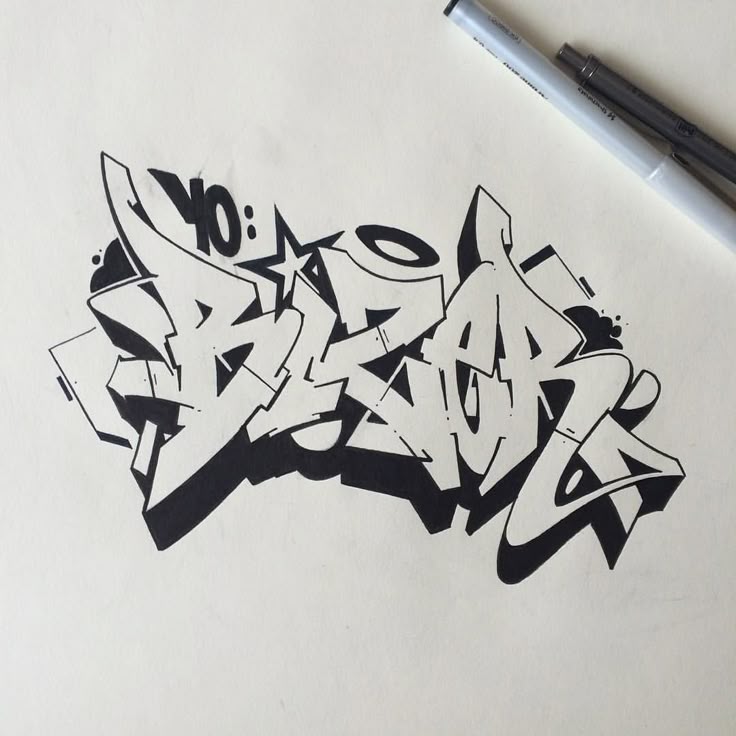
За потоком книжных новинок мы не успеваем задуматься над тем, что происходит с элементарной частицей любого издания – словом. А между тем оценка литературного процесса как “прорыва” или “кризиса” в глобальном смысле основывается на судьбе слова, его положении в современной культуре.
“Визуализация”, “визуальность” – эти понятия стали общим местом актуальной культурологии. Равно как и конкуренция между визуальной и словесной информацией, образом и словом, которое картинку только подразумевает.
Граффити, комиксы, инфографика, видеоблоги – многообразные подтверждения того факта, что слово в массовом сознании, массовом употреблении все более визуализируется. Для человека, воспитанного в прежнем, логоцентричном обществе, это не может не выглядеть унижением слова.
Но что если логоцентризм сменяется вовсе не визуальностью, а синкретизмом, сплавом художественных “языков”? Что если кажущееся унижение слова на самом деле направлено против перегородок, разделяющих разные области искусства?
В конце концов, субкультура граффити выросла из слова, в самом прикладном смысле – из авторского почерка. А визуализировать слово начала еще высокая поэзия – вспомним “рисунок стиха” Аполлинера, “лесенку” Маяковского, книжные эксперименты футуристов, фигурные стихи Вознесенского.
Материал нашего постоянного автора, искусствоведа и критика Веры Калмыковой, знакомит с языком рисованных слов.
Граффити: почерк на стене
Что может быть проще, однообразнее, скучнее, наконец, депрессивнее стены? Обычной стены в обычном городе, в чистом виде пригодной лишь для того, чтобы уставиться на нее в отчаянии. Узорная или грубая каменная кладка, деревянный или каменный же наличник, ветка чего-нибудь вечнозелено-вьющегося, нечто оживляющее, разбивающее жуткую, противную человеческой психике плоскость, – издревле известные украшения стены. Можно предположить, что первобытные наскальные рисунки несли ту же функцию, что в современном городе – граффити.
Наскальные росписи служили освоению мира. Тогда изображение воспринималось не так, как сейчас. Рисунок был не просто символом, “иконой” материального объекта – он мыслился как его неотъемлемая часть. Между художником и тем, что он изображал, через рисунок устанавливалась прочная связь, и художник – через посредника (изображение) – получал возможность непосредственно воздействовать на сам объект.
Искусство, по-видимому, не просто “вырастало из неискусства”, как принято считать, и изначально осознавалось не только как “нечто избыточное” для жизни (не пища, не тепло, не огонь, не деторождение…). Оно служило необходимым средством общения – между одной частью мира и другой. В этом его предназначение и в наши дни.
И если принять термин Якимовича как рабочий, то современные граффити – не что иное, как реплика: из первобытности в первобытность.
…Лет тридцать назад пяти-семиклассники захлебывались в упоении, рисуя на промокашках, на последних страницах или задних обложках школьных тетрадей разные слова. Именно рисуя, нарочито “толстыми”, похожими на слоников буквами, каждая из которых вдобавок словно “подлезала” под другую, из-за чего прочитать какое-нибудь “стол” или “Катя” становилось специальной работой. Разумеется, мы тогда и предположить не могли, что уже наши дети в сходном упоении станут разрисовывать (или расписывать) похожими буквами гладкие (и не очень), белые (и не очень) вертикальные поверхности зданий, бетонные заборы, гаражи et cetera. Слова “граффити” – ни с ударением на “а”, ни с ударением на “и” – мы тоже не знали. Хотя стоп, о чем это я? Знали, разумеется, применительно к древней истории: граффити (на первом “и”) – это древние (древнейшие) надписи или рисунки, оставленные доисторическими людьми, жителями какой-нибудь Месопотамии, или новгородцами, побывавшими, допустим, в храме Святой Софии…
То, что в древнерусских храмах на стенах написано нечто, после дешифровки прочитывающееся как “Здесь был Вася”, в расчет не берется: если надписи столько сотен лет, начинаешь испытывать к ней уважение как к факту высокой культуры.
Причем тут какой-то Вася?
Времена наших слонообразных букв нынче можно считать баснословными. Сегодня создание граффити является способом самоосуществления одной из молодежных субкультур и пользуется всем возможным вниманием. Существуют сообщества граффити, клубы граффити, сайты граффити, форумы граффити, фестивали граффити и бог знает что еще. Об истории граффити, о его основателях, о первых мастерах, о стилях и прочая можно прочитать в Интернете, набрав одно лишь слово в поисковике.
Не говоря уже о том, что продукты жизнедеятельности членов данной субкультуры встречаются мирным обывателям на каждом шагу. В практических целях нога ни одного из налогоплательщиков не ступит на полосу вдоль железнодорожного полотна – не станем же мы, солидные люди, там прогуливаться и старые гаражи тоже минуем, – но граффити на этом фоне бросается в глаза. А на павильонах теплосети? Фасадах магазинов?
Как одна из молодежных субкультур, граффити претендует на маргинальность и как бы бросает вызов обществу скучных в своей добропорядочности “взрослых”.
Даже само произношение (с ударением на “а”) – способ отмежеваться от словаря Ожегова, этакого воплощения общепринятого, находящегося вне субкультуры. И вот она – первая неясность. Что есть граффити? Только те нарисованные надписи, которые маргинальны и имеют характер вызова, или вообще все, что рисуется на стенах? И, кстати, что считать вызовом: политические лозунги, носящие, допустим, антигуманный характер, и неприличные изображения, допустим, половых органов (преимущественно мужских)? Или сам факт появления рисунков на вертикальной плоскости, непременной составляющей городского ландшафта?
Согласно словарным определениям, граффити считается всё, что появляется на упомянутых вертикальных плоскостях (вероятно, на горизонтальных тоже, хотя они менее предпочтительны). Вообще всё, без исключения. Преследующее цели эпатировать буржуа или раскрасить серые будни. Содержащее приличные или неприличные элементы изображения. Состоящее лишь из шрифтовых элементов и включающее в себя элементы традиционных изобразительных жанров – пейзажа, натюрморта или портрета, а также отсылающее к анимации или книжной иллюстрации (кстати говоря, отсылки к беспредметному в граффити – редкость).
Между прочим, в случае с рисунками слово “граффити” оказывается избыточным, так как подменяет и дублирует понятие “фреска”. Эти слова выступают как синонимы (тем более что и способы исполнения близки – с поправкой на высокие технологии, разумеется. Мастерство спреинга, например, произвело бы на какого-нибудь Микеланджело впечатление сильное, но, боюсь, неоднозначное).
И здесь сразу начинаются, так сказать, геополитические – или геосоциокультурные – различия. В одном из ближайших пригородов Парижа, городке Фонтене-о-Роз (полагаю, не только там), граффити-фресками покрыты почти все глухие торцы домов. Выходит на улочку, например, неинтересная стена. Вид, прямо скажем, не украшает. Нарисуем-ка на ней дверку, ветку дерева и клетку с птицей (реалистически так, высокопрофессионально) – и вся улица заиграет, и появится в городском ландшафте некая тайна, приманка-обманка, веселый и легкий мотивчик.
Все это разрешено и более того – финансируется городскими властями. Надоест горожанам дверка с птичкой – мэр отдаст распоряжение закрасить и придумать что-нибудь другое. Граффити это или нет? С одной стороны – да (во-первых, выполнено на стене, во-вторых, может быть изменено), с другой – нет: во-первых, санкционировано, во-вторых, традиционно, в-третьих, безлично: ни в прямом, ни в переносном смысле авторского почерка, а он в субкультуре граффити сакрализуется, здесь нет и быть не может.
…В российском городе Боровске сколько-то лет назад одному из местных жителей, художнику-любителю Владимиру Овчинникову, пришло в голову украсить глухие стены, нежилые или неухоженные здания сценами из местной истории.
Сюжеты там, прямо скажем, увлекательные: ведь в Боровске содержался мятежный протопоп Аввакум и была замучена боярыня Морозова, там же жил и творил великий Циолковский. Да и как в каждом более-менее крупном городе XIX – начала XX века, были там и пожарная команда, и разнообразные уездные учреждения, и купечество, и дворянство. И вот на стенах появились картины из славного прошлого. Со стихами, сочиненными Эльвирой Частиковой.
Является ли автор картинок мастером масштаба Репина? Прямо скажем, нет. Однако все, что он наизображал, глаз радует (или радовало, какой картинке как повезло). Человек он, между прочим, вовсе не юный, и отнести его к представителям молодежной субкультуры – большая натяжка. Кстати, когда Овчинников искал, каким образом выполнить указанные изображения, то пытался обратиться к технологии спреинга (разбрызгивание, распыление краски, принятое в субкультуре граффити), использовав баллончики. От этой мысли пришлось отказаться (получалось грубее, чем он хотел), нашел свое ноу-хау (правда, секрет не обнародовал).
Восстали против городских фресок Боровска не власти, не чиновники – сами горожане. Помню одного с рядом дивных железных зубов – прямо как в фильме про Джеймса Бонда. “Зачем мне, – говорит, – этот пожар на площади?” И вот горожане не пожалели сил, чтобы замазать или смыть “картины прошедшего”. Некоторые даже сподвиглись на ремонт фасадов. Уничтожено, конечно, не все, нет, но многое.
Как расценивать произведения Овчинникова: это граффити или фрески? Видимо, все-таки первое. Во-первых, потому, что фреска – это все же из области монументального искусства, созданного на века. А здесь сразу игра: вроде бы Овчинников хотел создать нечто долговечное, сделать согражданам этакий подарок, но ведь не мог не понимать, что дождь, снег, перепады температур и прочая свое дело сделают. И хотя ни технологически, ни поколенчески произведения самодеятельного художника из Боровска к граффити не относятся, два другие критерия – нелегальность и временность – оказываются в данному случае определяющими.
Третий пример – совсем недавний. Относится ли он к деятельности представителей молодежной субкультуры – опять-таки вопрос. То есть авторы себя позиционируют именно так. Речь о некоей акции группы “Война”, члены которой украсили фаллическим символом (выполненным, правда, для символа уж слишком натуралистично) известный разводной мост напротив известного здания известной организации в городе Санкт-Петербурге. За что и получили…
…денежную премию от государства. То есть маргинальное по исходному посылу деяние превратилось в одобренный правительством акт. Мейнстрима – поясняю, чтобы избежать двусмысленности. Резкий и механический переход из одного регистра в другой и сам по себе не прошел бы незамеченным, однако сопровождался еще и некоторым возмущением, так сказать, в массах.
Однако все это – крайние ситуации. Типичная же выглядит иначе: вооружившись баллончиками с краской, юные леди и джентльмены, будто пролетарии всех стран, соединяются, выходят куда-нибудь, где их, по возможности, не заметят или заметят не сразу, и начинают творить.
Интересно, что на стены, например, “сталинок” они не покушаются, зато на кирпичные трубы этих же самых домов – за милую душу. Существует несколько стилей граффити (любезные моим детским воспоминаниям буквы-слоники, “bubble letters” или “soft letters” – увы, позавчерашний день). Если в семидесятые на Западе шла настоящая “война стилей”, то сейчас ситуация несколько смягчилась, хотя стилистическое противостояние, разумеется, осталось. Нынче к этому виду изобразительной деятельности начинают обращаться профессиональные живописцы. Существуют национальные, региональные и прочие школы граффити. Есть “легальные” граффитчики – райтеры (их деятельность никого намеренно не шокирует, протекает в маргинальных, так сказать, городских зонах и потенциально не опасна для социума) и есть “нелегальные” бомберы (эти мажут где попало, могут залезть в тоннель метро и создать ситуацию, опасную для жизни). Но и те и другие – художники граффити.
И по большому счету бомберы – тоже ведь райтеры: название “бомбер” возникло только потому, что представителям субкультуры понадобилось отмежеваться от, так сказать, анархистов в собственных рядах.
Слова “райтинг”, “райтер” произошли от английского “to write”, и значит, непосредственно связано прежде всего с письмом, с буквой. Райтер – это писатель, даже если писатель всего одного слова. Но слово это одновременно – и изображение: если угодно, сразу и текст, и иллюстрация к нему.
Чисто визуальные произведения сливаются с граффити тогда, когда рисуются на улице как ее временное украшение. С граффити всегда так: или на следующий день к “испорченной” стене явятся возмущенные взрослые во главе с милицией (то есть уже полицией) и уничтожат изображение, или оно мирно пребудет на своем месте до тех пор, пока не исчезнет естественным путем или не будет закрашено, но не агрессивно, а так, по ходу жизни. Есть и третий вариант: стена исчезнет сама собой (стройка закончится или забор снесут – случается такое и с бетонными заборами).
Если сравнить, например, граффити с тату как разновидностью боди-арта, различие сразу бросится в глаза: тату “вечно”, уничтожить его можно только целенаправленно.
В этом смысле аутоакции русских футуристов выглядели иначе. “Исступленному городу дуговых ламп, обрызганным телами улицам, жмущимся домам – мы принесли раскрашенное лицо, старт дан, и дорожка ждет бегунов”, – писали авторы манифеста “Почему мы раскрашиваемся” Илья Зданевич и Михаил Ларионов. Тело понимается здесь тоже как некая плоскость, часть городского ландшафта – безликая, ибо подобна другим. Речь там также идет о строительстве, “песне о человеке”.
“Мы связали искусство с жизнью. После долгого уединенья мастеров, мы громко познали жизнь, и жизнь вторгнулась в искусство, пора искусству вторгнуться в жизнь. Раскраска лица – начало вторжения. Оттого так колотятся наши сердца.
Мы не стремимся к одной эстетике. Искусство не только монарх, но и газетчик и декоратор. Мы ценим и шрифт, и известия. Синтез декоративности и иллюстрации – основа нашей раскраски. Мы украшаем жизнь и проповедуем – поэтому мы раскрашиваемся” (цитируется по сборнику: “Русский футуризм: Стихи.
Статьи. Воспоминания”, СПб.: Полиграф, 2009).
Идею, что искусство “не только монарх”, что область его шире “высокого” ареала, XX век доказал, и современным художникам граффити нет нужды в подобной манифестации. Важнее другое – изначальная установка на временность, эфемерность, зависимость от внешних, внеэстетических факторов. Изменилось настроение – изменилась и раскраска. Стену можно побелить и записать наново. Ничего постоянного, вечного. В этом, пожалуй, одна из ярчайших примет “новой первобытности”.
Между прочим, если уж зашел разговор о “сталинках”: райтеры категорически против нанесения изображений на здания, имеющие свой стиль. Чрезвычайно чувствительные и к своей, и к чужой стилистике, они не трогают ни мемориальных зданий, ни машин (бомберы-варвары, конечно, эти запреты игнорируют, но на то они и варвары). Одно из правил райтеров гласит: “Те, кто пишет на чужих работах, заслуживают презрения. Единственное, чего они в итоге добиваются, – это как минимум огромного негодования и желания наказания хозяевами работ, со всеми вытекающими последствиями.
Отдельный и трудноизлечимый случай – это порча работ, тут мораль вообще бессильна: мало того, что живут в полном дерьме, так пытаются залить им все вокруг. Результат – презрение навсегда”.
Потому-то искусство граффити и маргинально: в “сити” любого города явно выражен стиль градостроителей, на окраинах же все значительно более нейтральное, “никакое”. “Никакое” можно сделать “каким-то”: а уже “какое-то” – только переделать, что в задачу райтеров, судя по всему, не входит. Тотальное перекрашивание мира, его коренная переделка – это не к ним: у них более локальная задача.
Мировая общественность, разумеется, делится на сторонников и противников граффити (тех, кому все равно, в расчет не берем). Противники организуют сопротивление, в основном – силами представителей других молодежных субкультур, что заставляет и граффити-любителей, и граффити-ненавистников плотнее смыкать ряды. Сторонники умиляются девизам граффити-фестивалей типа “Сделаем мир ярче”, “Крась!”, “Цветная планета”, будто детским рисункам, и разрабатывают конструкции архитектурных сооружений по модели граффити-буквиц тэгов (случай в Нью-Йорке).
Сами тэги, визуальные слова-знаки, изначально – своего рода “автографы” мастеров, формулы индивидуальных стилей, когда алфавит и манера его исполнения становятся способом представить себя миру.
Все это так странно знакомо: что-то подобное, кажется, было? Ну да, вот же: “1. Чтоб писалось и смотрелось во мгновение ока! 2. Чтоб писалось туго и читалось туго неудобнее смазанных сапог или грузовика в гостиной (множество узлов, связок и петель и заплат…)”.
И далее: “Живописцы будетляне любят пользоваться частями тел, разрезами,
а будетляне речетворцы разрубленными словами, полусловами и их причудливыми хитрыми сочетаниями… Этим достигается наибольшая выразительность и этим именно отличается язык стремительной современности, уничтоживший прежний застывший язык…”
Откуда это? Из манифеста “Слово как таковое”, подписанного А. Крученых и В. Хлебниковым.
А вот фрагмент позабористее: “Вы видели буквы их (писателей-нефутуристов.
– В.К.) слов – вытянуты в ряд, обиженные, подстриженные, и все одинаково бесцветны и серы – не буквы, а клейма! А ведь спросите любого из речарей, и он скажет, что слово, написанное одним почерком или набранное одной свинцовой (краской. – В.К.), совсем не похоже на то же слово в другом начертании. <…>
Есть два положения:
1) Что настроение изменяет почерк во время написания.
2) Что почерк, своеобразно измененный настроением, передает это настроение читателю, независимо от слов”.
Подписи те же: Хлебников, Крученых. Статья “Буква как таковая” из уже цитированного сборника “Русские футуристы”…
Конечно, надо сделать очень важное замечание: столетие назад футуристы, при прочих равных, делали установку скорее на слово звучащее, художники граффити сегодня – только на слово визуальное. Но причины, цели и задачи удивительным образом сходятся.
И, в общем, наметившееся противоречие возможно снять: слово имеет отношение к звуку речи, буква – к изобразительности.
Еще вопрос – насчет “мир ярче”. Граффити в покинутом Чернобыле и окрестностях даже на фотографиях выглядят как нечто инопланетно-жуткое. Будто на Марсе побывал, честное слово. Так что дело не только в яркости…
Многие райтеры – или те представители мирных обывателей, которые им покровительствуют, полагая, что легальный представитель субкультуры лучше нелегального, – считают, что их деятельность есть борьба с городским вандализмом (появилось даже выражение “креативный вандализм”: оксюморон, конечно, но знаковый). Лучше иметь на стене таинственную надпись, выполненную даже и в “диком стиле” (это когда буквы переплетены так, что разобрать и, соответственно, понять смысл написанного не представляется возможным), чем всем известное, набившее оскомину, но по-прежнему неприятное слово из трех (пяти, шести) букв, написанное, кстати говоря, совершенно без эстетического блеска (замечу в скобках: в Боровске крайне мало таких слов, написанных поверх фресок Овчинникова).
Но если это и так, то данный вид сопротивления варварам не подразумевает назидания. Собственно говоря, граффити по своей природе вообще не дидактично.
В самом деле: тэги – не слова, а тайнопись; крайне редко можно увидеть содержательную надпись, выполненную в стиле граффити. Какие-нибудь ура-патриотические призывы, националистические лозунги или такое вот, беспримерное: “Универсальная электронная карта – печать антихриста” – просто написаны, не тэгами. Но и восторженное “Я люблю тебя, Аленушка!” тоже, скорее всего, будет просто написано. Крупно, печатными буквами – не более того. Затронуть актуальные темы райтера можно побудить (допустим, в рамках антинаркотической кампании; а что, жить-то всем надо), но сам он вряд ли пожелает высказаться на злобу дня. Случаи, когда райтеры проявляют агрессию (допустим, сопротивляются тем, кто желает прекратить их художество), также редки (тем более что тогда это бомберы, а вовсе не райтеры). Проникновение на станции метрополитена с целью разукрасить поезда метро расценивается, как правило, именно как агрессия, но, полагаю, не в связи с поездами, а исключительно по причине реальной опасности данного вида транспорта и необходимости отслеживать и отлавливать диких энтузиастов.
Хотя известно, что первые мастера граффити обращали особое внимание как раз на метро: коммуникация, как ни крути, а ведь райтинг – способ общения, средство “опознать своих”.
Кстати говоря, художники граффити с готовностью переключаются на ночные клубы – если подвернется заказ и пара свободных стенок, в идеале расписанных (точнее, записанных, а еще точнее – зарайтованных) сверху донизу. Нелегал становится легалом, бомбер – райтером. Эпатаж – не самоцель, а средство достичь желаемого.
Цель же – самовыражение. Ничего нового: индивидуальность стиля, личный почерк, манера, идентичность тэга и его создателя нашли бы понимание и у какого-нибудь Фра Анджелико или Андреа Мантеньи, и у русских акмеистов. В этом смысле граффити – занятие сугубо традиционное, с теми же целями и задачами, что и у любого художника во все времена.
Еще одна цель – общение. Письмена райтеров, зачастую трудночитаемые, но рассчитанные на активное визуальное восприятие, непременно привлекают внимание, служат средством сплочения внутри субкультуры.
Это послание “к своим” – пусть и на непонятном для остальных языке. Это именно что визуальное слово-сообщение; важен образ, профиль и анфас тэга. Кто-то предпочитает готический шрифт, кто-то вручную стилизует компьютерные шрифты, допустим Tahoma или Times New Roman, – заинтересованный взгляд выявит единомышленников.
Однако еще интереснее другое. Граффити, неважно, райтинг или бомбинг, стали зарождаться (середина XX века) тогда, когда из мира постепенно начинал – только начинал! – уходить индивидуальный почерк. В самом прямом смысле: текст, написанный человеческой рукой. Заметим, что симптом проявился до начала болезни, чтобы не сказать пандемии.
Здесь надо сделать небольшое методологическое отступление. Не стоит, несмотря на соблазны, воспринимать граффити только как визуальное искусство. Это не так. Пусть это тайнопись – но это все равно картинка+. И, безусловно, высказывание, даже очень простое, например: “Это – Я!” (как у Ницше: “Прежде всего, не путайте меня с другими”).
Граффити – это язык, знаковая система, визуальная формула текста, а не изображение из букв. Эта система развивается параллельно с литературой и имеет с нею общий источник – слово как таковое, слово как нечто сакральное. В эпоху, когда и литература, и слово десакрализуются, широкое бытование граффити симптоматично. Да, это другая коммуникация. Но – коммуникация, нравится нам или нет.
И если почерк Петрарки со временем превратился в курсив и входит ныне во все версии текстовых программ мира, то почему бы не предположить, что через какое-то время буквы-“слоники”… Молчу, молчу.
…Примерно в семидесятые-восьмидесятые индивидуальный почерк стал потихоньку оживать в рекламе – как знак живого присутствия, как пресловутое “Здесь был Вася”. Но это была капля в море, предпоследнее “прости” миру, где мелкая моторика еще оставалась напрямую связана с мозговой деятельностью.
Последнее прозвучало позже. Несколькими десятилетиями позже, после начала компьютерной эры.
Ситуация стала в этом смысле и вовсе катастрофической. Мы больше не пишем писем – мы их набираем. Покинув стены средней школы, мы забываем, для чего в магазине канцтоваров продается предмет под названием “ручка”. Все компьютеризировано. Дошло до того, что от современного писателя не остается рукописей, максимум – компьютерная распечатка без следов авторской правки.
В России история возникновения и распространения граффити имеет дополнительные особенности. Русская народная культура, может быть, даже сильнее, чем какая-то другая, во всяком случае, из европейских, очень завязана на визуальный элемент. Росписи внутри городских домов еще каких-нибудь сто пятьдесят лет назад были не редкостью – нормой. Росписи стен домов или заборов (это помимо деревянных наличников!) – тоже.
Но мы-то! По древнерусским рукописным и печатным книгам мы знаем, с каким тщанием украшались развороты инкунабул (это примета, разумеется, и европейского Средневековья).
Мы знаем стенописи храмов и имена их авторов. Но вот городской или деревенский ландшафт мы представляем себе очень плохо, поскольку не имеем хоть в слабой мере сохранившегося материала. А он, ландшафт этот, был ярок и многоцветен. Честь и слава, например, художнику Евгению Розенблюму, который при создании Егорьевского историко-художественного музея воссоздал интерьер богатого купеческого дома, изнутри покрытого росписями. Значительно менее доступный простому смертному пример – интерьер Грановитой палаты Московского Кремля.
Так что граффити в Европе выступает средством сохранения индивидуальности, а в России – еще и продолжением, странным и причудливым эхом традиционной культуры.
Обе эти задачи скорее экзистенциальны, чем социальны. Русское “узорочье нарочитое” сегодня никак не обусловлено социальными обстоятельствами, а о сохранении человеческой самости и говорить нечего: общество всегда было ярым противником “я”, выбивающегося за усредненный порог.
Дело в другом: появившись параллельно с основным течением культуры, как письменной, так и визуальной, развиваясь внутри общества и одновременно вне его, независимо от основных идей мейнстрима, искусство граффити стало, при всей своей программной эпатажности, той единственной, наверное, на сегодняшний день чисто эстетической деятельностью, которая практически уничтожена постмодернизмом, отрицающим эстетическое как таковое. Изготовление объектов вместо произведений не подразумевает незаинтересованного наслаждения – оно прогнозирует совсем другие реакции, ждет их и питается ими. Эстетическая деятельность ради себя самой возможна лишь тогда, когда цель искусства – создание произведения, и ничего больше.
Оттого-то граффити в Чернобыле – при всем шокирующем впечатлении – совершенно естественны: глядящие в пустоту лица несуществующих людей замкнуты на самих себя, они не нуждаются в зрителе. Они – не предупреждение, не напоминание, не социальный призыв. Они – свидетельство ужаса происшедшего.
Ужаса, осознавшего себя.
В самом деле: можно заплатить райтерам-участникам фестиваля за раскрашенный фасад блочного дома. Но нельзя продать этот фасад или рисунок на части бетонной стены. То есть саму-то плиту – пожалуйста, но именно как плиту, строительный, допустим, материал. Можно продать, подарить, сдать в аренду гараж, покрытый граффити, – но именно как помещение для автомобиля, а не как “холст” или “доску”, на которой создана, допустим, алтарная картина или цветочный натюрморт. Потому что если мы дарим кому-то граффити, то они тут же перестают быть таковыми, поскольку перестают быть частью городской среды. В этом смысле мало какая субкультура так далека от идеологии потребления, как деятельность поклонников граффити.
Получается, что общество, пытающее легализовать райтеров, приручить их, с одной стороны, узаконивает их присутствие в городском ландшафте, за счет чего улучшается данный ландшафт, а с другой – на корню губит сам принцип граффити.
Создавая “вторую природу” на час, на день, на год, на несколько лет, художники граффити не просто преобразуют пространство, отрицают торжество пустой стены или ищут, с кем бы побегать по крышам. Они – почти без агрессии – выступают за право на параллельный общесоциальному вектор жизни. Они воплощают индивидуальное, совершенно никому не нужное индивидуальное в условиях, когда это становится все менее и менее возможным.
Так что пусть лучше остаются маргиналами: целее будут.
∙
Граффити (Palm OS)
Жесты, используемые на оригинальных портативных компьютерах Palm OS
Граффити по сути одноходовой стенография распознавание почерка система, используемая в КПК на основе Palm OS. Граффити было первоначально написано Palm, Inc. как система распознавания GEOS -на основе устройств, таких как HP OmniGo 100 и 120 или Волшебная шапка -line и была доступна в качестве альтернативной системы распознавания для Яблочный Ньютон MessagePad, когда NewtonOS 1.
0 не очень хорошо распознавала почерк. Граффити также наносится на Windows Mobile платформу, где он называется «Block Recognizer», а на Symbian UIQ платформа в качестве распознавателя по умолчанию и была доступна для КПК Casio Zoomer.
Программное обеспечение основано прежде всего на неография символов верхнего регистра, которые можно рисовать вслепую стилусом на сенсорной панели. Поскольку пользователь обычно не видит персонажа во время его рисования, в четырех самых сложных буквах устранены сложности. «A», «F», «K» и «T» все нарисованы без необходимости совмещать перекрестный штрих.
Некоторые буквы можно нарисовать не «официальными» штрихами. Двумя примерами этих альтернативных штрихов являются буквы «V» (нарисованные одинаково только справа налево) и «X» (нарисованные так же, как буква «K», за исключением перевернутых справа налево). Эти альтернативные ходы часто распознаются с большей надежностью.
- 1 История
- 2 Версии не для Palm OS
- 3 Иск
- 4 Смотрите также
- 5 Рекомендации
- 6 внешняя ссылка
История
Граффити было разработано Джефф Хокинс, который ранее создал «PalmPrint» (систему распознавания символов, используемую Casio Zoomer[1]) распознавать естественный почерк.
[2] Используя более простой алфавит, компьютеры могли легко распознавать почерк. Хокинс считал, что люди потратят время на изучение граффити так же, как люди учатся. сенсорный. Хокинс вспоминал свою догадку: «И тут она пришла ко мне в мгновение ока. Сенсорная печать — это навык, который вы учиться.» [2]
Хокинс также предусмотрел единую область для написания букв друг на друге.[2]
Хокинс назвал эту систему «PowerPalmPrint» или P3. Другие инженеры Palm переработали и расширили алфавит, созданный Хокинсом. Джо Сифер и Рон Марианетти создали больше символов и знаков препинания, а также разработали прототип Graffiti, который запускался на ПК с периферийное устройство для планшета.[2]
Версии не для Palm OS
Граффити также было нанесено на Яблочный Ньютон. В 2008 году неавторизованная версия Graffiti была представлена для iOS (iPhone и iPad ) устройства. An Android Версия была выпущена в 2010 году японской компанией ACCESS Co.
, Ltd., которая приобрела права на Graffiti после приобретения PalmSource, Inc. в 2005 году.[3]
Иск
Первоначальная система граффити была предметом судебного иска от Ксерокс, утверждая, что она нарушила патент Xerox в отношении ее Unistrokes технологии (Патент США 5,596,656 , выдана в 1997 г.). Технология Unistrokes была изобретена в Исследовательский центр Пало-Альто (PARC) Дэвида Голдберга в 1993 году.[4]
Позже Palm обжаловала первоначальное решение суда как по иску о нарушении патента Xerox, так и в отношении действительности патента в первую очередь. Апелляционный суд вынес решение в пользу Xerox в отношении первоначального решения о том, что Palm нарушила патент Xerox, но отправил дело обратно в суд низшей инстанции, чтобы решить, был ли патент действительным с самого начала. В 2004 году судья вынес решение в пользу Palm при рассмотрении патента, заявив, что патент Xerox недействителен на том основании, что «ссылки на предшествующий уровень техники предполагают и делают очевидным заявление».
«Xerox получает от PalmOS». Австралийский. 4 июля 2006 г. Архивировано с оригинал 13 февраля 2009 г.
внешняя ссылка
- Граффити для Android
- Приложение Graffiti Height Fixer
Дизайн в стиле граффити
3 — 2006
Марго Григорян
Авторский почерк
Работа
Алгоритм творчества
Инструменты
Peepshow
Заказчики
Выставки
Вдохновение
Заказы, рассказы
На счету у британского художника-иллюстратора Майлса Донована (Miles Donovan) несколько сотен работ, выполненных по заказу самых разных компаний и издательств. Он участвовал в семи крупных выставках и стал основателем популярного творческого объединения Peepshow. Его иллюстрации украшают корпуса американских самолетов. За ним охотится Шэрон Осборн. И теперь он согласился дать интервью нашему журналу.
Авторский почерк
Стиль Донована узнается с первого взгляда.
Фотореалистичность объектов и портретов, яркие пятна краски, четкие линии и сбалансированные композиции вот несколько характерных черт художественного стиля этого иллюстратора. Чемто его работы похожи на граффити. Но это и не удивительно: Донован действительно использует в своей работе приемы граффитистов. В частности, распыляет краску через трафареты. Иллюстратор говорит, что его стиль это сочетание старого с новым, а именно традиционных техник рисования с возможностями, которые дают современное программное обеспечение и оборудование.
Работа
Донован понял, что хочет профессионально заниматься иллюстрацией и графическим искусством, около десяти лет назад, когда готовился к поступлению в вуз и обучался на специализированных курсах. Степень бакалавра искусств он получил в Брайтонском университете.
Художник рассказывает, что поворотным в его карьере стал момент, когда он начал работать в цифровом пространстве.
«Несомненно, это привнесло больше возможностей в мою работу, а также сделало творческий процесс более гибким, говорит Донован. Но я бы никогда не смог полностью отказаться от техник, предполагающих ручную работу. Нестабильность, самобытность, а иногда и простота ручной работы позволяют достигать эффектов, которые невозможно сымитировать в компьютерной программе».
Плакат «1XTRA Hip Hop Weekend 2005», выполненный по заказу Blue Source/BBC, 2005
Рассуждая о требованиях и стандартах современной коммерческой иллюстрации и графического дизайна, Донован говорит, что сейчас уже стало правилом: конечный результат работы должен быть представлен заказчику в цифровом виде. По его мнению, причина этого кроется в быстром развитии технологий за последние годы. «Несомненно, это влияет на процесс работы иллюстратора, считает Донован. Причем не только на стиль, но и на рабочий график. Сроки исполнения заказа становятся все более сжатыми, и приходится работать быстрее».
Рабочий день Донована протекает организованно и четко. В студию он приходит к девяти либо к половине десятого. Сначала совещание с коллегами за чашкой утреннего чая. На переписку, чтение новостей и Интернетпорталов у художника уходит около часа. К одиннадцати часам Донован приступает к работе. Трудовой день заканчивается для него, как правило, в семь или восемь вечера. Однако иллюстратор признается, что часто забирает домой ноутбук и продолжает работать там допоздна.
Эскиз для майки «CMYK 2», сделанный для японской компании Graniph, 2005
Промо-иллюстрация «Sweet no sugar» для агентства Art Department, 2005
Алгоритм творчества
Донован говорит, что описать процесс создания иллюстраций ему очень непросто. Дело в том, что для каждой конкретной работы художник выбирает свою уникальную технику исполнения.
«Это очень длительный процесс, включающий множество экспериментов с техникой и материалами», рассказывает Донован.
Однако, какой бы ни была работа, без программ Adobe Photoshop и Adobe Illustrator Донован не обходится. Некоторые заказы иллюстратор выполняет полностью в цифровом пространстве. Но все же намного чаще процесс создания иллюстраций включает как цифровую, так и рукотворную стадии. В любом случае каждый проект начинается с подбора необходимой графической информации. В первую очередь это фотографии различных объектов и героев, которые Донован отыскивает в Интернете, в печатной прессе либо в своих личных архивах.
Излюбленная техника Донована весьма специфична. Сначала в программе Adobe Illustrator он создает макеты для трафаретов, помещая каждый элемент изображения в отдельный слой. Когда макет готов, художник распечатывает трафареты, вырезает их вручную и заливает краской. Когда краска высыхает, Донован сканирует все листы, открывает оцифрованные фрагменты будущей работы в программе Adobe Photoshop и там объединяет их в цельную композицию.
По словам художника, этот процесс может занимать очень много времени.
Работу «Coney Island-The Cyclone» Майлс Донован сделал в свое удовольствие — пока она нигде не публиковалась, 2006
Иллюстрация «Access» для проекта «Crossfields Issue 1: Access», по заказу Wire Design, 2004
Инструменты
Для своей работы Донован использует Adobe Photoshop CS и Adobe Illustrator CS. В техническом арсенале художника компьютеры Power Mac G4 и PowerBook G4, мониторы Mitsubishi и LaCie, принтеры Epson и сканеры Canon и Heidelberg. Донован говорит, что сканеры в его руках очень быстро выходят из строя. «Они либо оказываются залитыми краской, либо попросту перестают работать после того, как я, например, переворачиваю их и в таком состоянии сканирую, скажем, шкаф с документами, рассказывает иллюстратор. Сканеры издают совершенно потрясающие звуки, когда пытаешься заставить их работать не по инструкции!»
Рабочие инструменты художника, несомненно, привели бы в восторг школьного учителя труда.
Это всевозможные ручки и чернила, золотые аэрозольные краски Montana, монтажный клей, изоляционная лента, проволока, клейкий офисный пластилин Blu Tack и даже хирургические перчатки. А для вырезания трафаретов он использует специальный коврик и скальпель.
Peepshow
В 2000 году Донован основал творческое объединение Peepshow, куда вошли также шесть студентов Брайтонского университета, специализирующиеся в области иллюстрации, анимации и графическом дизайне. Спустя два года к ним присоединились еще пять профессионалов. Среди клиентов этого творческого объединения такие компании, как Toyota, Diesel, Selfridges, BBC и др. Сегодня Peepshow работают в студии в Лондоне, которую они называют своим домом. Однако заказы каждый из членов Peepshow принимает индивидуально.
Заказчики
Список клиентов, по заказу которых Донован выполнял иллюстрации, поражает не только своим размером, но и наличием в нем всемирно известных названий.
В их числе такие периодические издания, как Cosmogirl, Dazed and Confused, Elle, Financial Times, Forbes, GQ, Guardian, Independent, Men’s Health, New York Magazine, Seventeen, Telegraph и Timeout. Есть среди клиентов Донована и настоящие монстры шоубизнеса: Atlantic Records, Inside Entertainment, J Records, Maverick Records и Warner Bros. Ему также заказывали работы The British Council, Hodder Stoughton, Leo Burnett, Penguin, Sleep Airlines и многие другие.
Заказы поступают Доновану не только из Великобритании, но и из США, где его представляет ньюйоркское агентство Art Department. Художник говорит, что американские клиенты в большинстве своем отличаются от британских тем, что предпочитают быть осведомленными о каждом этапе проделываемой работы и тщательно отслеживают весь процесс. Кроме того, они часто вносят свои коррективы, дабы работа в точности соответствовала поставленной задаче. Донован считает, что эти изменения сказываются на художественной ценности иллюстраций.
А вот британские клиенты, по словам иллюстратора, в гораздо большей степени готовы предоставлять свободу для экспериментов с техникой и стилем. «На самом деле все это мелочи, и различие между американскими и британскими клиентами не так уж и велико, говорит Донован. Самая большая проблема при работе с американскими заказчиками заключается в разнице во времени. Часто мне приходится задерживаться на работе до одиннадцати часов, чтобы координировать работу с клиентами из США».
В поисках новых заказчиков Донован устраивает множество промоакций через творческое объединение Peepshow. Немало помогает ему в этом и его собственный вебсайт http://www.milesdonowan.co.uk. Подобно многим современным графическим дизайнерам и иллюстраторам, Донован активно рассылает образцы своих работ потенциальным заказчикам. А через агентство Art Department в НьюЙорке он распространяет печатные рекламные материалы. «Обычно для рассылок рекламных и промоматериалов я тщательно отбираю образцы своих работ, учитывая специфику каждого потенциального заказчика», говорит художник.
Рекламный постер «Smitty» для нью-йоркской компании J Records, 2005
Рекламный плакат «Mashonda» для нью-йоркской компании J Records, 2005
Иллюстрация «Cam’ron» для журнала Source, 2005
Выставки
Донован принимал участие в семи крупных выставках. В 2004 году в галерее Phonica Gallery в Лондоне состоялась персональная экспозиция иллюстраций Донована «Fact Presents Art: Miles Donovan». А совсем недавно в лондонской галерее Menier Gallery прошла выставка под названием «4Wall: New Voices», где было представлено пятьдесят работ двенадцати иллюстраторов и художников, широко известных во всем мире. Целью экспозиции было сделать их искусство более доступным для среднего класса: на выставке продавались не только оригиналы, но и репродукции работ по доступным ценам.
Вдохновение
Донован называет несколько имен творческих деятелей, вдохновляющих его сегодня.
Это фотограф Джамель Шабазз, художник Джефф МакФетридж, режиссер и сценарист Майк Миллс, режиссер Майкл Гондри, режиссер, актер и сценарист Спайк Джонз, графический дизайнер, типограф и режиссер Сол Басс, автор детских книг и иллюстратор Мирослав Шашек и художник комиксов Джек Кирби. «А еще меня вдохновляют регулярные поездки в НьюЙорк, откровенничает Донован. Мне нравится целыми днями гулять по городу, теряться в его улицах и фотографировать».
Донован рассказывает, что в годы учебы вдохновение свое он черпал из работ таких художников, как Энди Уорхол, ЖанМишель Баския и Жан Дюбюффе. «В то время профессия иллюстратора, равно как и Интернет, еще не были популярными, рассказывает он. Поэтому основное влияние на меня оказывали художники, работы которых я рассматривал в альбомах из библиотеки».
Заказы, рассказы
Доновану больше всего нравится выполнять заказы, имеющие отношение к музыке.
«Я всегда с радостью берусь за заказы, тематика которых мне интересна», подчеркивает иллюстратор.
Один из самых интересных заказов Донован получил от Гая Осири, бизнеспартнера Мадонны по компании Maverick Films. Художнику было поручено выполнить сто иллюстраций портретов музыкальных звезд к книге Осири «On the Record». На работу художнику отводилось всего две недели. «Я совершенно не представлял, как сделать все в срок! рассказывает Донован. А после того, как книга вышла в свет, мне пришлось избегать телефонных звонков от Шэрон Осборн по вопросам копирайта. Она жаждала моей крови! С этой женщиной лучше не связываться».
Еще один увлекательный проект Донован выполнил совсем недавно. Компания Target Stores выкупила все рекламные площади в одном номере журнала The New Yorker и заказала ведущим мировым иллюстраторам работы, включающие логотип и прочие элементы корпоративного стиля компании. «Техническое задание было достаточно свободным, что всегда радует», подчеркивает иллюстратор.
Художник также рассказал о самом необычном заказе, над которым ему доводилось работать. Авиакомпания AirTran заказала ему портрет сэра Элтона Джона, чтобы поместить его… на корпуса своих самолетов. «Изображение по размеру получилось таким же, как голова статуи Свободы, говорит Донован. Очень странно думать о том, что моя работа летает над США на двадцати самолетах на высоте двадцати тысяч футов!»
КомпьюАрт 3’2006
«Если бы не закрашивали, пропал бы интерес»: разговор с граффити-художниками
В России уже давно процветает стрит-арт: граффити можно заметить практически в каждом дворе. Но что за люди украшают стены наших городов? Уличные художники Beat.c, Gesh, Blot и Крутое Пике рассказали, как они начинали рисовать и чем вандализм отличается от искусства.
Почему для уличных художников важна анонимность?Beat.
c:
У нас, как и в большинстве стран мира, несогласованное рисование на улице преследуется законом, я просто не хочу проблем.
@beat.cc
Gesh:
В России рисование, можно сказать, запрещено — легальных стен почти нет, их можно по пальцам пересчитать. К тому же кроме стрит-бомбинга (граффити на стенах и зданиях — Прим. ред.) есть еще трейн-бомбинг (граффити на поездах — Прим. ред.). Если с первым все еще не так плохо, то за второе наказание довольно серьезное. А так как я принимаю участие и в том и в том, лучше позаботиться о своей анонимности, чтобы не было лишних проблем.
Крутое Пике:
Чаще всего я рисую на улице, в местах, где это запрещено. Не хочется иметь проблемы с властями.
Как выбирается никнейм?Beat.c:
Мой псевдоним сложился механическим образом. Долгое время в начале моего творческого пути я посвятил исключительно рисованию букв.
За этот период мной были изучены техники построения и преобразования шрифта. Исходя из этого опыта я сложил оптимальную последовательность символов, с которой мне удобно работать.
Gesh:
Просто открыл английский алфавит и выбрал буквы, которые, как я подумал, мне будет интересно рисовать.
Крутое Пике:
Давно, лет десять назад, придумал себе никнейм — Пикезо. Я тогда еще учился в художке, и мне показалось забавным исковеркать фамилию известного художника и применить к себе. Потом, с годами, убирал и подставлял новые буквы и в итоге пришел к тому, что есть. Сейчас полный никнейм — это Крутое Пике.
Blot:
Я работаю под псевдонимом Blot, этот никнейм из детства. Во дворе мы придумывали своих супергероев и играли в них, именно так и звали моего персонажа. Когда я впервые пошел рисовать на улице в 2008 году, я подписал так свой рисунок — с тех пор и пользуюсь этим никнеймом.
@beat.
cc
Beat.c:
Свой первый рисунок на стене я сделал весной 2009 года. Выходит, на данный момент я рисую 11 лет. В последнее время часто размышляю о техниках и подходах к работе, ищу новые способы реализации своих идей. К примеру, недавно попробовал работать со скульптурой и мозаикой. А еще занимаюсь иллюстрацией в своем стиле. Ну и само собой, о граффити стараюсь не забывать.
@beat.cc
Gesh:
Рисую я с 2012 года, начинал вместе со своими друзьями. Именно они меня и позвали в первый раз — но в итоге они забросили, а я продолжил. Я стараюсь развиваться во всех направлениях, но больше всего внимания уделяю буквам: все-таки это классика граффити.
Крутое Пике:
Я занимаюсь стрит-артом уже лет 13. Было много перерывов. Пробовал и абстракцию, и коммерческие работы. Но сейчас ушел в классику (классическим направлением граффити считается теггинг, нанесение тегов, то есть никнейма, слов, букв — Прим.
ред.). Очень люблю шрифты, стараюсь каждый раз добавить что-то новое в свой шрифт, при этом оставив его узнаваемым.
Blot:
Рисую с 2008 года. Я начинал с академизма, потому что в детстве учился в художественной школе, а потом в институте изучал академический рисунок, основы живописи, композицию. Но мне не хватало творческой свободы. Желание творчески раскрепоститься пришло с первым походом на стену.
Самым первым моим рисунком был персонаж — собственно, я до сих пор рисую персонажей с метафорическими высказываниями. То есть мой первый шаг был началом того, что я делаю до сих пор.
Все мое творчество — это поток изменяющихся эмоций и мыслей. В 2015 я сделал свой первый фасад пятиэтажного дома. Мой самый большой страх — это высота, а для того, чтобы реализовать эту идею, нужно было работать с автовышки. На протяжении всей работы я испытывал дичайший страх. Но мне все-таки удалось ее реализовать — и я считаю, что вполне удачно. В такие моменты, когда ты перебарываешь себя, начинаешь больше радоваться тому, что удается.
@sashablot
@beat.cc
@gesher_uno
@kpytoe_peake
@sashablot
Как относишься к тому, что твои работы закрашивают?Beat.c:
Жизнь граффити бывает коротка в двух случаях: если художник осознанно мирится с тем, что его работу закрасят наутро, и если он не понимает, где его рисунок или тэг уместен, а где нет.
Я стараюсь выбирать места, которые меньше подвержены тому, чтобы быть закрашенными быстро. К примеру, недавно рисовал на заброшенном здании, фасад которого выходит на шоссе. Это очень просматриваемое место, вокруг постоянная пробка из автомобилей, но вот здание это уже никому не нужно. Другой вопрос, что ради этого пришлось рисовать валиком вниз, лежа на краю крыши, что не очень удобно. Однако в этой ситуации я понимаю, что усилия оправдывают результат.
Gesh:
В этом есть свой шарм. Конечно, прикольно, когда, приезжая, видишь свои работы.
Но все в нашей жизни скоротечно, поэтому отношусь к этому как-то по-философски.
@sashablot
Крутое Пике:
Я считаю, что если бы их не закрашивали, то пропал бы интерес. Конечно, очень обидно, когда ночью ты сделал крутое место, а с утра приехал его сфоткать, и бам… уже все закрашено. Но бывает и такое, когда работа на видном месте висит несколько лет.
Blot:
Со временем я начал спокойно к этому относиться. Это улица, открытое пространство, и если ты делаешь работу в публичном месте, которое не принадлежит тебе, то нет ничего удивительного в том, что ее могут рано или поздно закрасить.
Когда-то меня это и правда напрягало, потому что ты вкладываешь силы и время, а работу закрашивают, и все сводится к нулю. Но ты же идешь не только за результатом, а еще за процессом, за вдохновением, за атмосферой. Соответственно, ты реализуешь свои цели, которые даже важнее, чем то, что работу могут закрасить.
Ради чего все это? В чем смысл твоих работ?Beat.
c:
Когда человек только начинает рисовать, всегда присутствует азарт: быть самым узнаваемым, популярным, чтобы все видели и знали, что вот такой персонаж есть. Зачастую это связано с подростковым максимализмом, примерно в этом возрасте большинство будущих членов субкультуры в нее и попадают. Со временем вырабатываются индивидуальный почерк и тактика рисования.
Для меня это доступный способ заявить о себе окружающим: «Вот он я».
При этом перед художником граффити есть две задачи: пробиться сквозь назойливый шум городской рекламы и в то же время сделать это эстетически красиво — как минимум для тех, кто в этом что-то понимает. И все это — в реалиях архитектуры коробочно-кирпичных домов и зачастую неумелого, непродуманного градостроения. Получается целая наука — где-то пересекается с архитектурной деятельностью, где-то с графическим дизайном. Только вот нет никаких брендбуков, дедлайнов, очереди согласований и вечно недовольного руководства.
Вообще очень интересно наблюдать, как власти пытаются выживать граффити из городской среды. Частое закрашивание рисунков толкает людей изобретать интересные способы как можно дольше сохранять граффити на их на месте. Некоторые на стенах города уже 20 лет — и это прямо в центре Москвы!
Gesh:
Для меня граффити — это процесс и знакомства.
Очень классно то, что ты можешь приехать в любой город мира и там найти людей, которые просто занимаются тем же, чем ты, и встретят тебя, как своего.
Крутое Пике:
Я не стараюсь найти для себя какой-то смысл. Не поддерживаю какую-то идею. Я просто делаю то, что люблю. Я люблю эту движуху в целом. Для меня общение так же важно, как и рисование. На самом деле у нас очень большое комьюнити: у меня есть много знакомых из других городов и стран.
Blot:
Прежде всего ради себя: я вижу в этом способ самореализации. Я достаточно интровертный человек, а рисуя на улице и на зданиях, — там, где люди могут это увидеть, — я высказываюсь.
Это некий диалог и с самим собой, и с людьми, которые это видят.
Я испытываю большое удовольствие от самого процесса рисования в открытом пространстве. Нигде больше такого нет: ни в студии, ни в мастерской. Там тоже есть свои плюсы, но именно на улице и в заброшенных зданиях я получаю удовольствие от нанесения краски на стену, на интересные фактуры. Это необычные материалы на необычной поверхности. И если ты понимаешь, что ты сделал именно то, что ты хотел, — это такая «пилюля радости».
Я люблю работать с формой, мне важно передать через форму настроение, идею, взять несколько аспектов и совместить их во что-то одно. Мне нравится иносказательность, метафоричность, когда ты можешь глубокий смысл внедрить в минимальную форму. Лучше говорить простым языком о чем-то сложном, нежели сложным о простом.
@gesher_uno
Где грань между искусством и вандализмом?Beat.c:
По мне, нет никакой грани, оба этих явления могут свободно пересекаться между собой, взаимодополнять друг друга.
Искусство — понятие расплывчатое. Существует идея и ее реализация; если для реализации идеи нужно заняться вандализмом, то я не вижу в этом ничего деструктивного.
Помню, что внешний вид Москвы при Лужкове гораздо больше страдал от океана уродливых вывесок и рекламы, чем от граффити. А какая за этим стояла идея? Что-то продать. Стоит в данном случае одно другого? Такие вопросы мне кажутся куда важнее.
Gesh:
Она, наверное, у каждого своя. Хотя у настоящих райтеров есть внутренние правила, где не надо рисовать, например — на памятниках, мраморе и тому подобном. А те, кто обычно занимается подобными вещами, чаще всего просто взяли баллончик или маркер первый раз в руки и никак не связаны с граффити.
Лично я не люблю называть то, чем занимаюсь, искусством, мне кажется это высокомерным. Я обычно говорю, что просто делаю то, что мне нравится, а как это называется, мне уже неважно.
Крутое Пике:
Я думаю, эта грань очень субъективна.
Есть вещи, которые точно можно отнести к искусству, о других же можно смело говорить — вандализм, но вот в граффити мне сложно провести эту грань.
Blot:
Вандализм тоже может быть искусством. Искусство — это не только созидание, разрушать тоже можно красиво и интересно.
Наверное, нужно думать о мотивах: цель вандализма — что-то уничтожить и испортить, ничего не создавая. А можно, разрушая, создавать что-то красивое. Разбить окно тоже можно красиво. И в трещинах и разрухе можно найти много красоты. Думаю, тут вопрос в мотивах и концепции действий того или иного автора.
Яркий пример — рисование на электричках и поездах. Художники по сути занимаются вандализмом: закрашивают окна, портят вагоны, но при этом рисунки и шрифты могут быть дико крутыми. То есть это стык искусства и вандализма, все в одном флаконе.
@beat.cc
@sashablot
В стрит-арте есть какие-то правила?Beat.c:
Опять же — смотря что считать стрит-артом.
Человек, занимающийся стрит-артом, выполняет работу чуть более сложную, чем граффитчик. Задача последнего — написать свое имя, а вот первый стремится в тех же уличных условиях донести до зрителя конкретную мысль.
Отрасль более широкая, потому что художнику стрит-арта подвластны все форматы и материалы. Хоть скульптуру выставляй на улицу. А вообще, на мой взгляд, какие тут могут быть правила? Как говорится, кто во что горазд.
Если человеку что-то действительно интересно, его зацепило, то правила — это дело времени. Сейчас 2020 год: информации навалом, развиваться можно очень быстро. Главное — это искреннее желание и голова на плечах.
Gesh:
Мне кажется, нет такого, что нужно знать обязательно. В граффити рамок нет, как и в рисовании. Ты можешь нарисовать все, что захочешь.
Тут есть связь с твоим поведением: если в жизни ты быдло, которое никого не уважает, то и в граффити ты будешь быдлом. Такие вещи зависят от конкретного человека.
Крутое Пике:
Основные правила — это не перебивать рисунки других, если, конечно, они не перебили тебя до этого.
Я перебиваю очень редко. Мне нравится делать по чистой стене, да и в городе обычно места свободны. А вот на лайнах (ж/д линии — Прим.ред.) чаще всего все занято, поэтому там сложнее. Начинать всегда нужно с бумаги, дальше пробовать в заброшках или легальных стенках, набивать руку.
Blot:
Может быть, и есть какие-то правила, но я о них не знаю и сам стараюсь себя не ограничивать. Думаю, любому, кто хочет пойти рисовать на улицах, нужно забыть о правилах и максимально эгоистично к этому относиться. Правило, которому, наверное, стоит следовать: я хочу, чтобы ко мне относились так, как я отношусь к другим. Если ты не хочешь, чтобы тебя закрашивали другие, не делай так сам.
В любом случае, стрит-арт и граффити — это максимальная свобода, без рамок. Поэтому я бы не стал здесь чем-то ограничиваться, тем более придуманными кем-то правилами.
Проверьте, что вы узнали:
Что такое стрит-бомбинг?
Это «налет» на одну улицу сразу нескольких художников
Это выход художника на разведку по улицам района, чтобы выяснить, на каких стенах можно рисовать
Это рисование на стенах домов
Это особый метод рисования, когда жидкую краску брызгают на стену из банки, а не из баллончика
Что считается «классикой» граффити-искусства?
Теггинг — изображение имен, слов, букв
Портреты
Рисование только контура предметов, без заливки
Повторение известных шедевров живописи
Некоторые художники считают, что есть поверхности, на которых нельзя рисовать.
А где точно можно?
На мраморе
На железнодорожных путях
На памятниках
На чужих работах
Как относится к граффити российское законодательство?
Запрещены любые виды стрит-арта
Запрещен только трейн-бомбинг
Есть легальные стены, но чаще всего граффити запрещены
Никак не относится, законы не регулируют такую деятельность
Далее
”Сейчас этот поезд тронется”. 15 граффити, которые удивляют реализмом: 25 сентября 2020, 13:13
25 сентября 2020, 13:13
9
Глядя на невероятные рисунки, оживившие бетонные стены, поражаешься, насколько большой путь прошел уличный стрит-арт, превратившись в настоящее искусство.
TengriMIX предлагает взглянуть на впечатляющие трехмерные оптические 3D-иллюзии.
Мы уже рассказывали о 44-летнем португальце Серхио Одейте. Он родом из города Дамаи, расположенного в пригороде Лиссабона. Мужчина с детства любит рисовать, а с 1996 года стал пробовать себя в граффити.
Граффити-художник заинтриговал пользователей Сети снимком бетонного блока
Посмотреть эту публикацию в Instagram
Публикация от ODEITH (@odeith)
Посмотреть эту публикацию в Instagram
Публикация от ODEITH (@odeith)
Художник продолжает экспериментировать и удивлять людей своим творчеством.
У него более 774 тысяч подписчиков в Instagram, которые с нетерпением ждут его новых работ.
Посмотреть эту публикацию в Instagram
Публикация от ODEITH (@odeith)
Посмотреть эту публикацию в Instagram
Публикация от ODEITH (@odeith)
Автор называет свой стиль «мрачный 3D». Действительно, большинство его работ жизнерадостными не назовешь. Его персонажи, будь это животные, насекомые либо предметы, имеют суровый вид и совсем не вызывают у зрителя улыбку. Однако чувство восторга смотрящему гарантировано.
Потому что у Серхио уникальный почерк.
Посмотреть эту публикацию в Instagram
Публикация от ODEITH (@odeith)
Посмотреть эту публикацию в Instagram
Публикация от ODEITH (@odeith)
Рисуя, он акцентирует внимание на рельефе, тенях, свете и глубине изображения, что превращает вроде бы обычное изображение в невероятную оптическую иллюзию. В результате его работы кажутся живыми и словно вот-вот вырвутся из стены.
Посмотреть эту публикацию в Instagram
Публикация от ODEITH (@odeith)
instagram.com/p/B884mMupogX/?utm_source=ig_embed&utm_campaign=loading» data-instgrm-version=»12″>Посмотреть эту публикацию в Instagram
Публикация от ODEITH (@odeith)
По его словам, самой сложной картиной, которую он нарисовал за последнее время, оказался вагон поезда. Было очень сложно передать все его цвета, чтобы он выглядел реалистичным.
Посмотреть эту публикацию в Instagram
Публикация от ODEITH (@odeith)
Посмотреть эту публикацию в Instagram
Публикация от ODEITH (@odeith)
«Я не всегда испытываю вдохновение, пытаюсь его черпать из разных тем, таких как природа и различные объекты, чтобы создать что-то новое и необычное», — признается уличный художник.
Посмотреть эту публикацию в Instagram
Публикация от ODEITH (@odeith)
Посмотреть эту публикацию в Instagram
Публикация от ODEITH (@odeith)
Ему нравится быть безумным и бросать вызов самому себе. Начинающим художникам, чтобы добиться успеха, он рекомендует быть дисциплинированными и стойкими.
Ночные «бомбы»